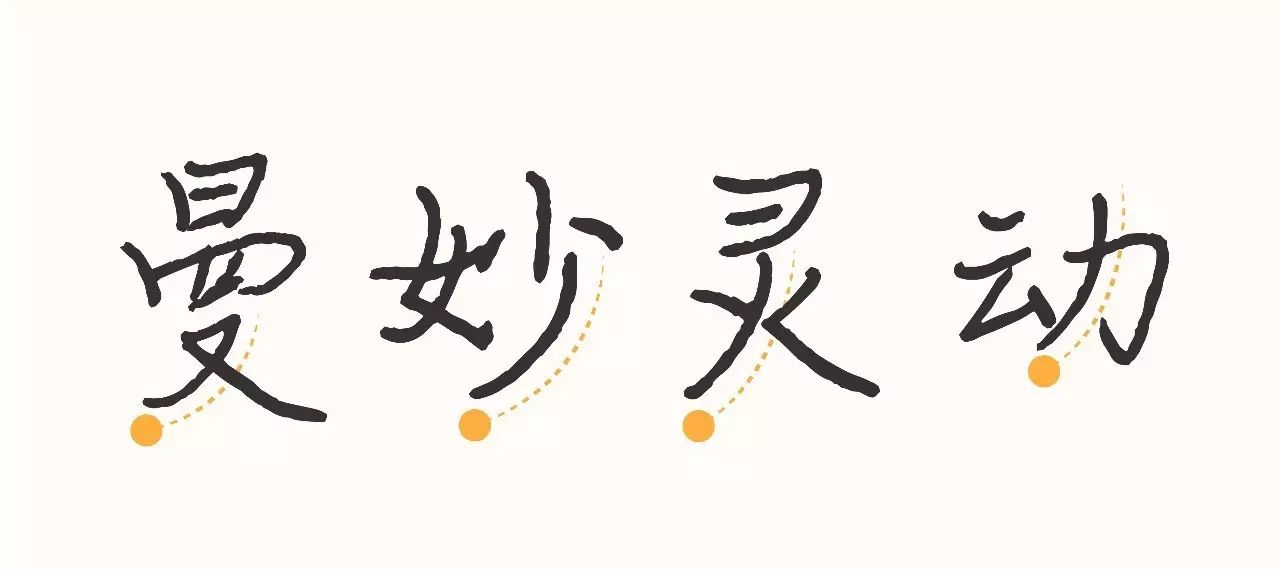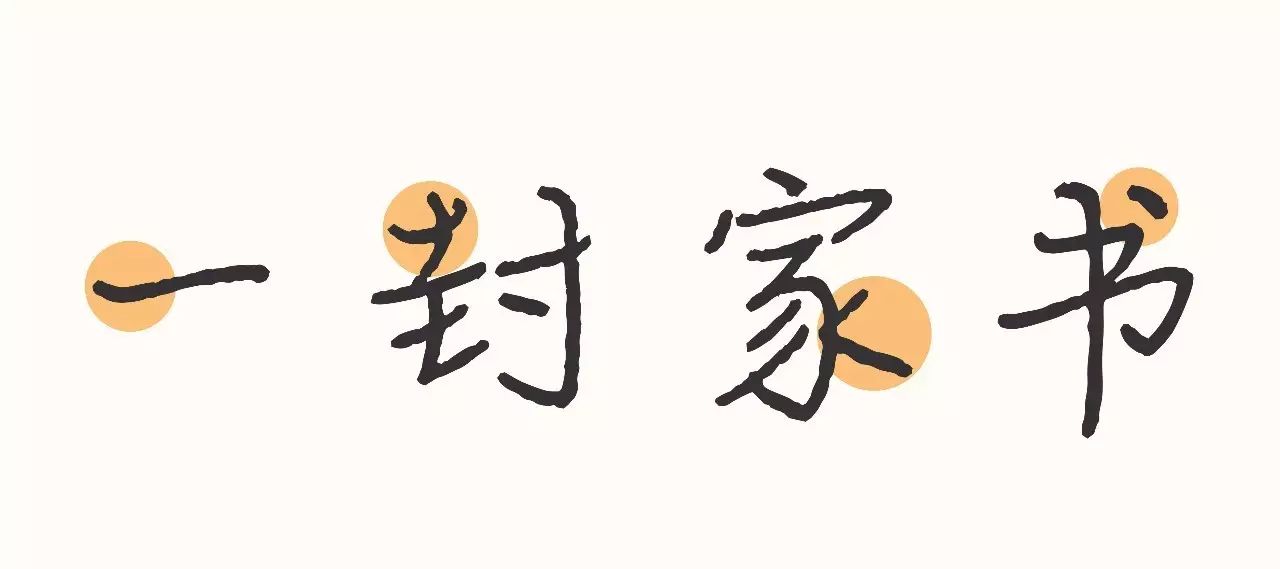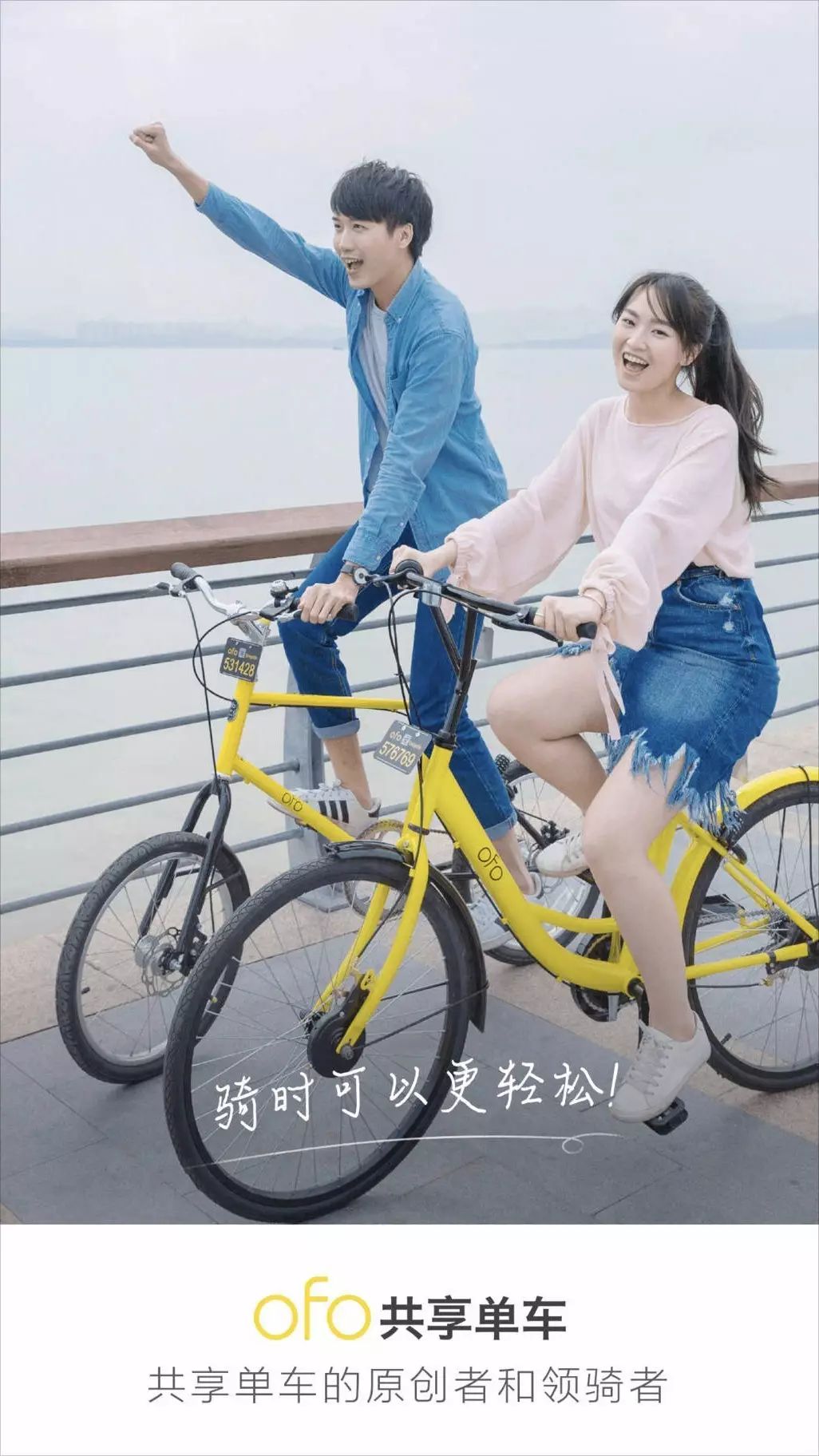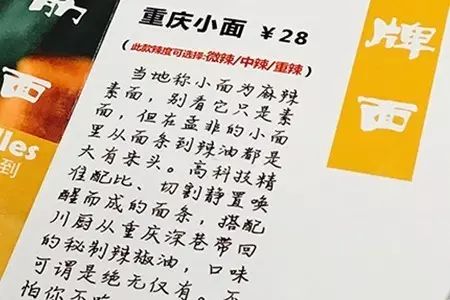
这个妹子不简单
说起手写字体现在曝光率相当之高,汉仪尚巍手书、方正德年行书、叶根友刀锋黑草、文悦青龙体等等各个堪称字体界的网红,但这些字太过个性只能用于标题中,用在正文中就略显不足。这也就是我介绍晨妹子的理由,一款适用于正文阅读的手写书法体。
邻家女孩手写风
晨妹子共收录中文9169字,西文及数字符号等731字, 作为一款有着女性风格的硬笔书法字体, 字体中融入了欧体的笔法结构,如大家熟知的 天覆者凡画皆冒于其下, 地载者有画皆托于其上等。
晨妹子字稿展示
而在笔画上晨妹子只是保留欧体撇捺转折起伏的笔势,融入了对书法的理解毕竟人家一个妹纸总要写出一些婉转轻灵的感觉,若是一味追求欧体笔画特点反而失去了创作的本意。
晨妹子笔画特征
手写韵味十足
应用效果
作为一款如此清秀自然的字体用在书信、文章等轻松语境中在合适不过了,就在前不久晨妹子与ofo(小黄车)首次牵手亮相,也是博得众人青睐。这里小编也做了收集。
ofo小黄车应用
“孟非的小面”菜单应用
那么,这么一款有温度的手写字是出自哪位小姐姐之手呢?献出一个小彩蛋,晨妹子出自汉仪字库美女设计师张照晨,不是开玩笑,有图有真相哦!(微博更精彩,关注需谨慎~)小编只能帮你到这了 ~
晨妹子设计师张照晨